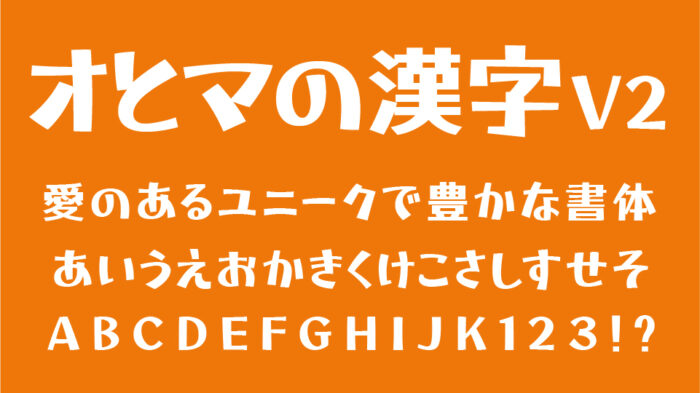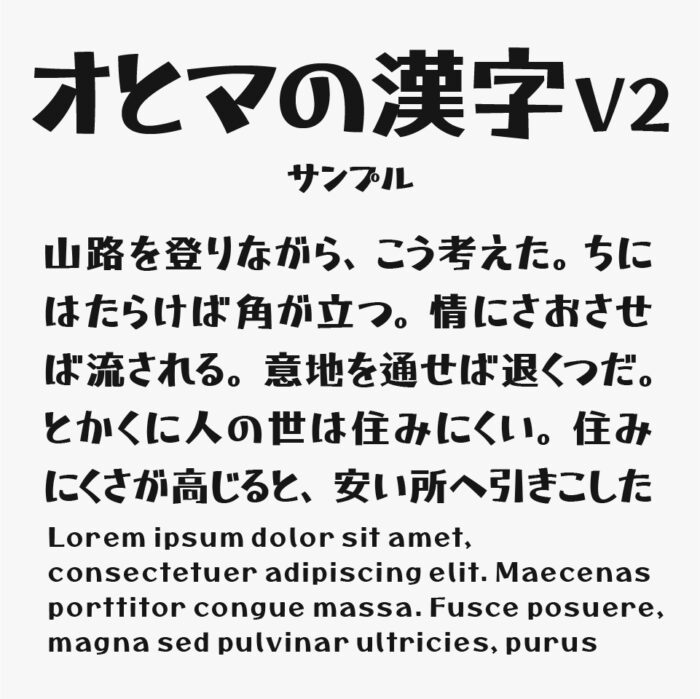
オとマの漢字V2
オとマの漢字V2フォントは、オとマのペフォントに不足している漢字や記号を補うために、改変した「M PLUS 1」を混植して仕上げられたフォントです。
マンガの効果音のような特徴のオとマのペフォントが持つかわいらしい縦横ストロークの丸みを残しつつ、「M PLUS 1」の改変も絶妙に調整されているため、二つのフォントが自然にミックスされた仕上がりになっています。